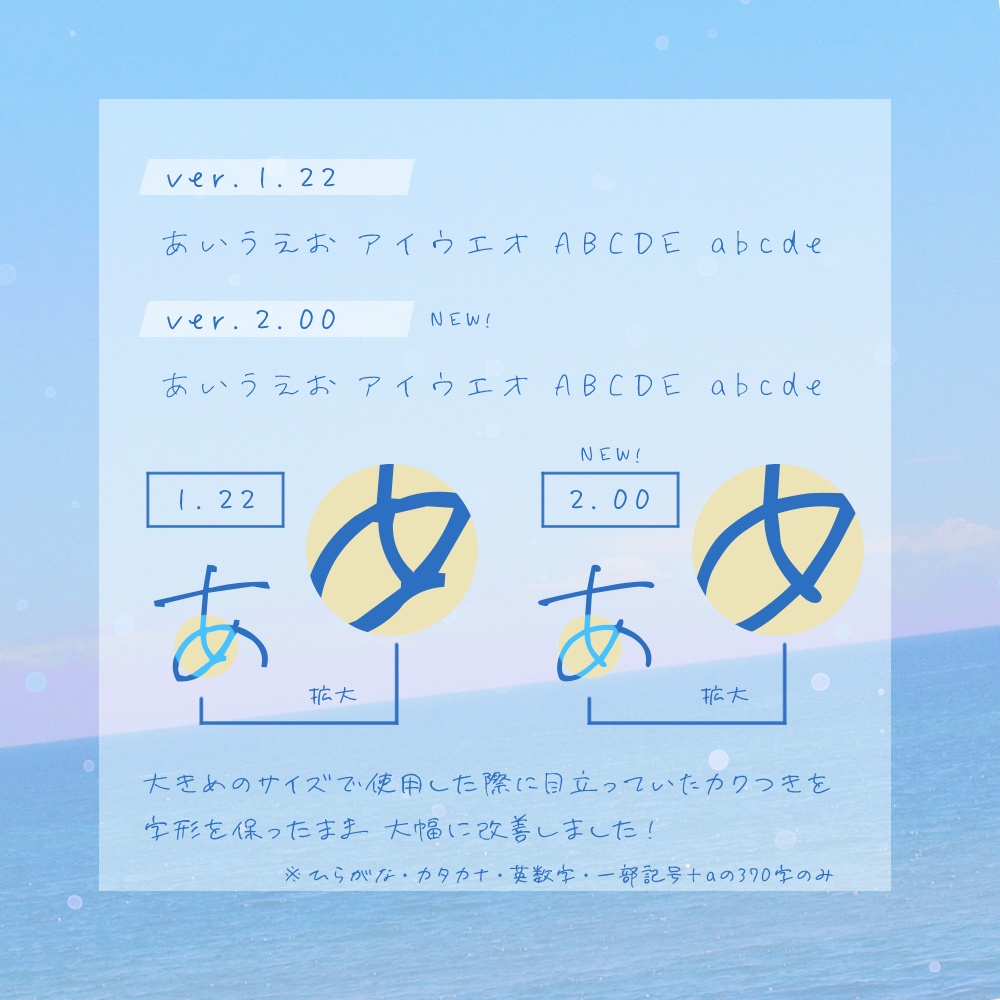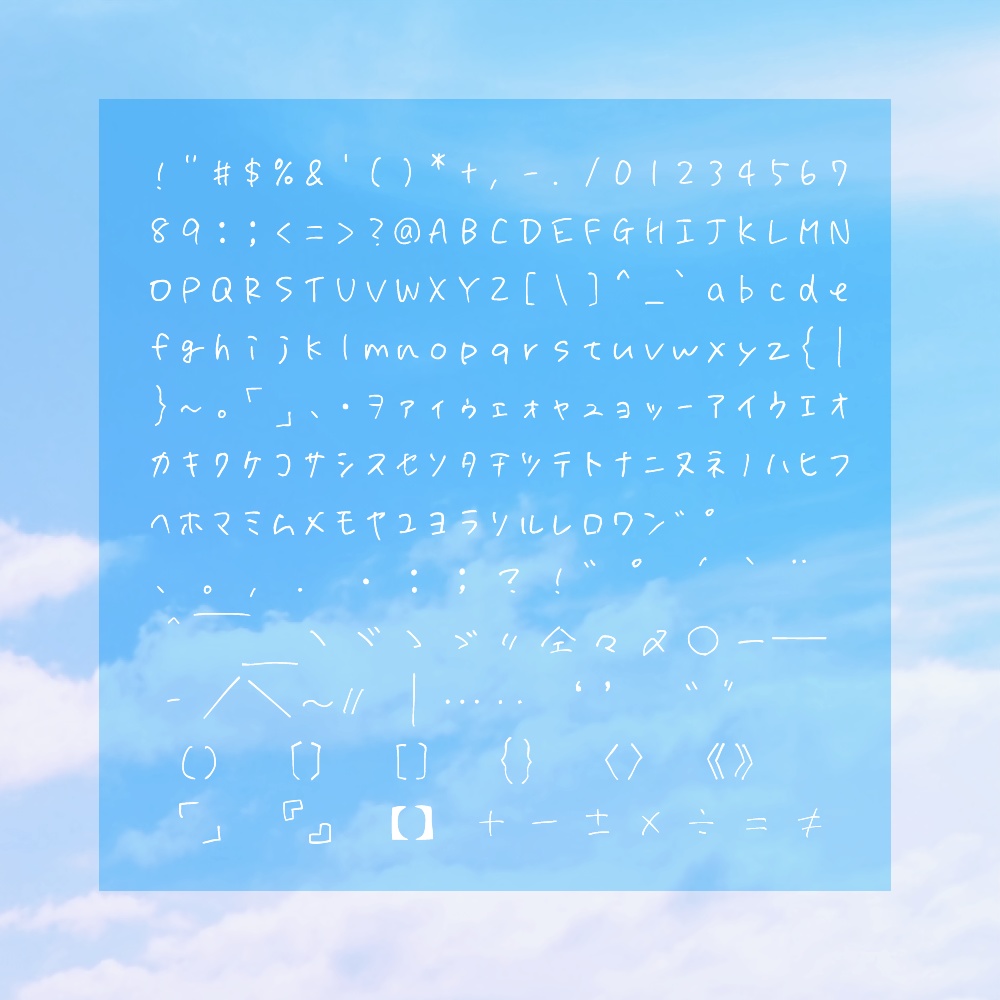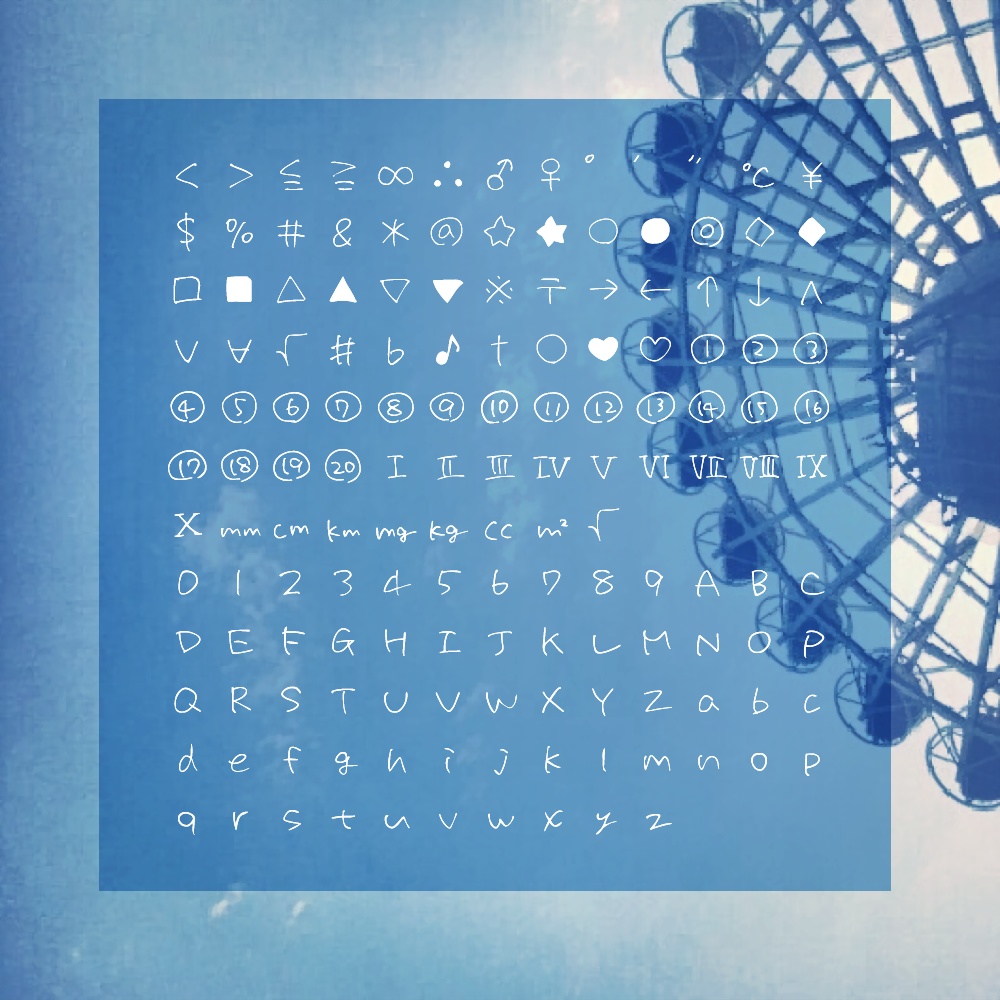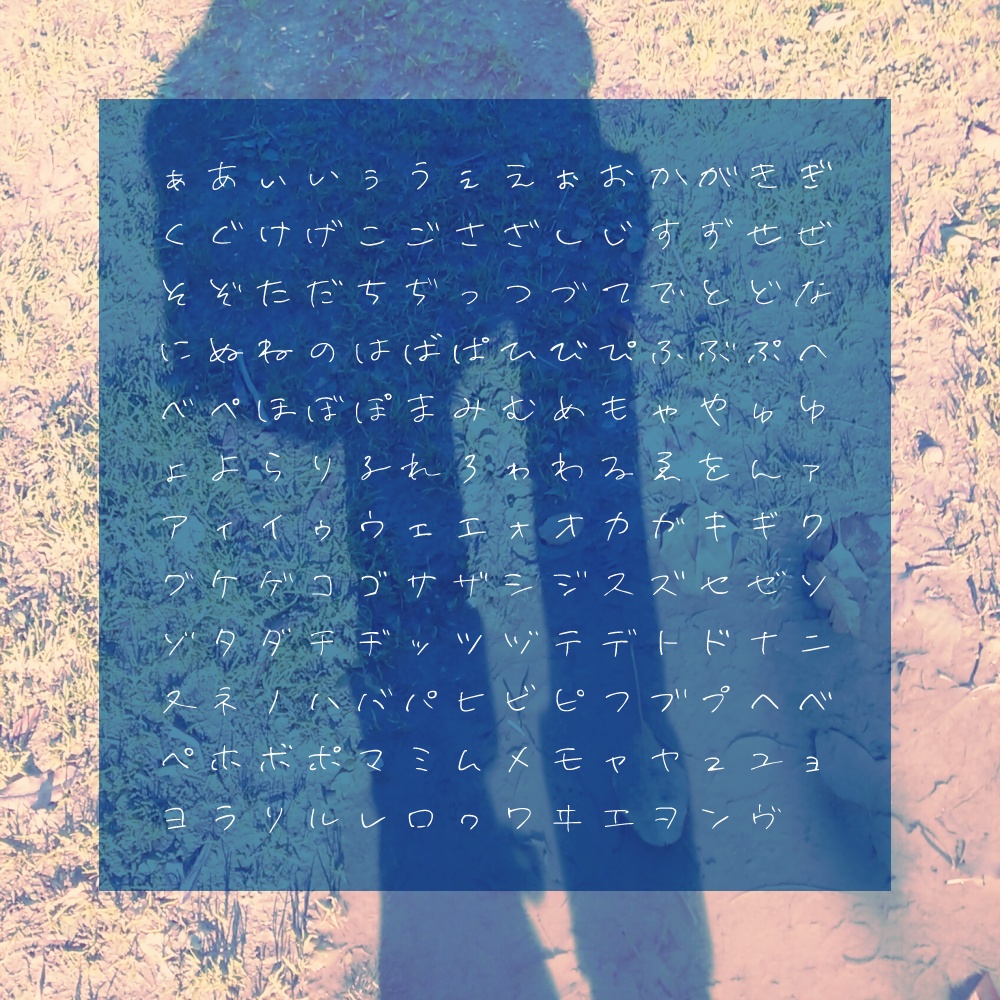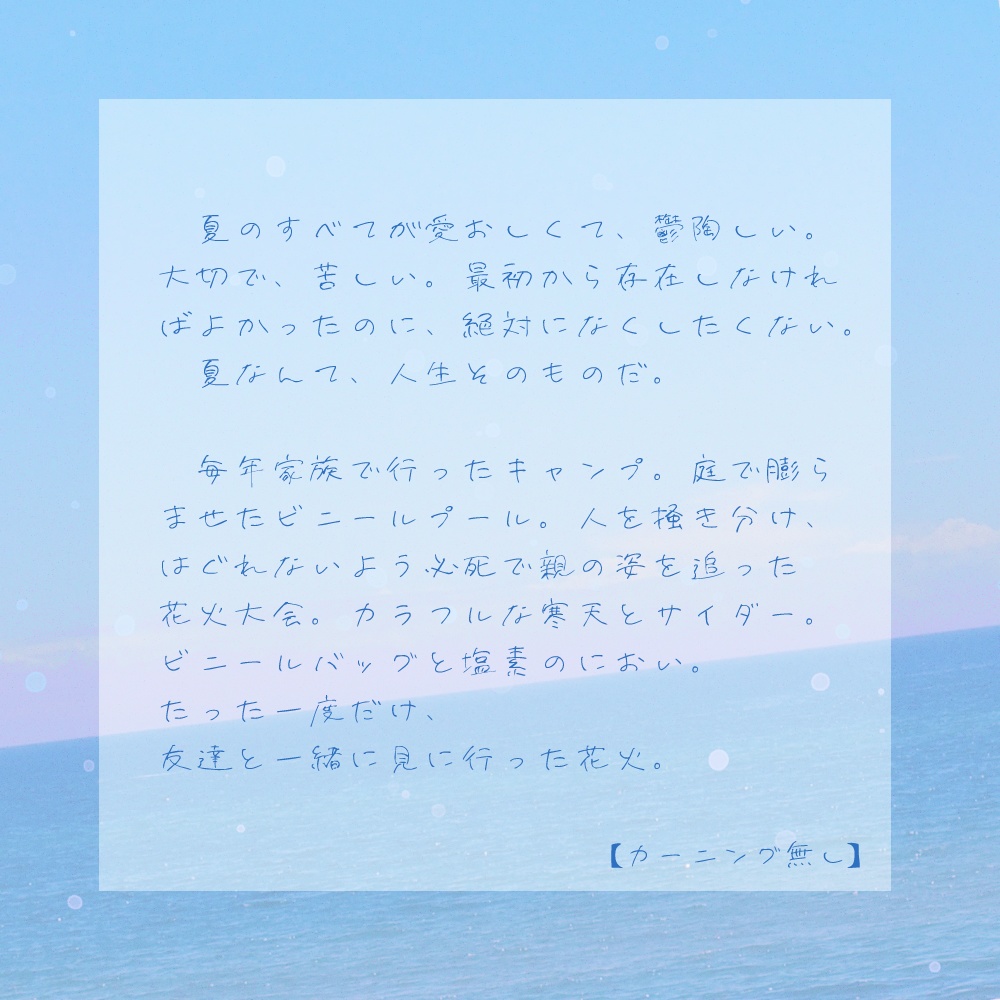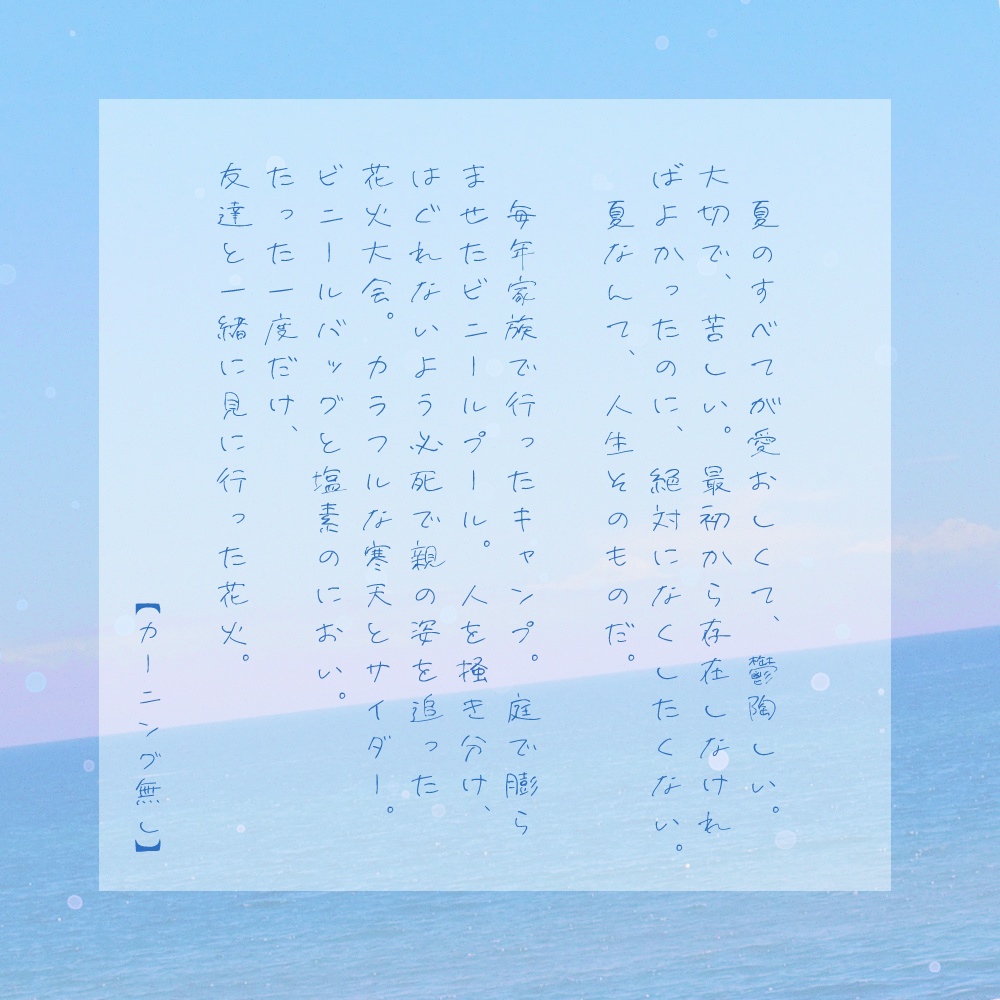
【フリーフォント版】アイシングソーダ2.04
こちらのフリー版は【 商用利用禁止 】です。 商用でのご使用には商用版ライセンスをご購入ください。 DL前に必ず下記URL先より利用規約のご確認をお願いいたします。 https://berrymilksugar.com/font/ ---------------- * 24.07.15 ver.2.04にアップデートしました。 漢字を3字追加し、一部文字の字形やバランスを修正しました。 * 24.01.02 ver.2.02に大型アップデートを行いました。 フォント名が【 アイシングソーダ2 】になりました。 23.01.16 に商用版にて先行リリースしていたものです。 フォントサイズ大きめで使用した場合、縁のカクつきが目立つ特性を大幅に改善。 なるべく字形を保ったまま(一部意図的に調整を入れているものもあります)、以前までは直線的だった縁部分を、自然な曲線に見えるよう調整を行いました。 上記の改善はひらがな・カタカナ・英数字・一部記号+αの371字のみに対応しています。その他の字形に関しましては、基本的に今後の対応予定はございません。 また、以前までは縦書きレイアウト時に専用文字として表示されていた一部字形を、通常の字形と統一しました。 フリー版アップデートにあたり、漢字を6字追加しています。 ---------------- cuteとemotional、どちらも諦めない方へ。 【エモかわいい】の方角を目指したフォントです。 インク溜まりの見える、ボールペンでざっと書いた雰囲気を持たせています。 癖のある丸さでかわいさを残しつつも、現代の若さ、青さに宿るエモーショナルを打ち出しました。 一文字ずつ手書きしており、直打ちでも手書き感が出るよう配慮して制作しています。 ・TrueType形式 / 等幅フォント / Windows11にて動作確認済み ・収録文字はひらがな、カタカナ、英数字、各種記号、JIS第1水準漢字、JIS第2水準漢字の一部。 合計 3778文字 ・フォントサイズ小さめでの使用を推奨。サイズを上げるほどカクつきます。 ・今後不定期にアップデートの可能性あり 本ファイルは武蔵システム( https://opentype.jp/ )の TTEdit を使って作成しました。 ---------------- 【投げ銭版】 https://berry-milk-sugar.booth.pm/items/3221201 【商用版】 https://berry-milk-sugar.booth.pm/items/3221320 もあります。 お気に召しましたら、なにとぞよろしくお願いいたします。 SNS等でのシェアもとても励みになります……!